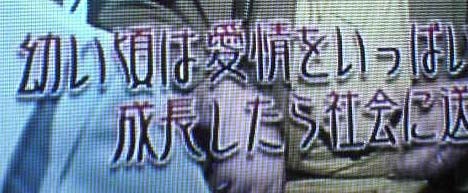
10年前のインタビュービデオを拝見して  tomoppyこと河原  2008年10月4日(土) 10:42  Mail
[タイプラボ・フォントNEWS]第58号のMLで紹介された佐藤さんの映像を拝見しました。貴兄のMLを受けるようになってから5年以上にもなると思いますが、いつも楽しみに記事を読ませて戴いています。
映像の中にお話のあった超職人気質のお気持ちは立派で、感心しました。また、どの職業についても言えることですし、Fontを制作される世界も絵画などと同様の評価がなされていることの世界だと気づかされました。今後のご発展を願っての感想でした。
メルマガもWEBサイトも、いつも文字や画像だけのお知らせですので、たまには声や映像などでリアルな感じをお伝えしたくなり、今回の記事となりました(10年以上前の映像ではリアルと言えないか…)。
メルマガで案内してから丸二日過ぎましたが、300人ほどの方が見てくれたようです。
著作権違法かどうかの判断  山田ナオタカ  2008年9月11日(木) 0:11  HP
フォントについての著作権違反かどうかの判断はどうやって付けたらよいのでしょうか。
たとえば、http://www9.atwiki.jp/gamekouryaku-knst/pages/37.htmlのサイトのように、
明らかに、
・HG明朝B
・HG重ね角ゴシックH
・HG重ね丸ゴシックH
・魚石行書?
・HG創英角ポップ体
・HG創英角ゴシック
を加工したり、
MSゴシックを代用したりするのは、
法律上、著作権に違反するのでしょうか。
サイト管理人に違反のおそれがあるので注意をしたのですが、
聞く耳を持っていただけませんでした。
注意しても駄目な、こういう人いますね…。
フォントを作る…ってことは、この程度のことだと思ってるんでしょう。
どうしても気になるのでしたら、当事者(権利保有者)に連絡して、そちらから警告してもらうしかないでしょう。
なるほど、やはりその方法になるのですね。
私も以前フォント制作に携わる機会がありましたが、
一字一字作っているということを認識してほしいと感じました。
例のサイトをさらに調べてみると、
どうやら、英文字についても、こちらのサイトのフォントを
あたかも自分の成果物のようにふるまっていることがわかりました。
http://blog.mix-tune.com/archives/319.php
このサイト、なくなったようですね。
山田ナオタカさんの行動の影響なのか、当事者からの警告があったのか判りませんが、悪質なフォント配布サイトがひとつ減ったことは確かです。
同じ管理人が、サイト名を変えて同じようなコトをしていないことを願います。
【フォントの価格ってどうなのよ】読みました。  2008年6月1日(日) 23:47
大変興味深く拝読しました。
そして世の中には “安いから” 使われるフォントが溢れているなあ、と再認識。
以外に一般の方はフォントの美醜に興味がなく、大半の書類張り紙にMSゴシック。
テレビのテロップも大半がスクリーンフォントの権利が安価なものに見えます。
確かにそれも文化の一つ、私も会社っぽい雰囲気を出したいときにわざとMSゴシックを使ってみたりすることもあります。
でも逆に美しいフォントがたくさん使われている環境だったら…。特に子どもたちには大きな影響があるような気がします。わたし個人がフォントに興味を持ったきっかけも児童文学に使われていた活版の文字、漫画のセリフの写植、絵本の文字等からでした。
一概に、安い=悪いと言えないのがフォントではありますが、「文字を読む」という、社会で暮らしていく中ですごく重要な行動を支えているものなので、もっと注目されるべきであるとは思います!
価格が高いフォントが優れている…と言い切る事もできません。
美意識とか美的感覚、機能性など、使う人によってフォントを選ぶ基準はさまざまだと思います。
・フォントの価格が、もう少し低い価格帯に収まっていれば、一般の人達にもっと興味を持ってもらえるのじゃないか。
・購入者には関係ない、制作期間や費用などを安易に価格に転嫁しないで欲しい。
そういう気持ちで今回の原稿を書きました。
【フォントの価格ってどうなのよ】読みました。  2008年6月2日(月) 19:59 [修正]
>・購入者には関係ない、制作期間や費用などを安易に価格に転嫁しないで欲しい。
作る側はなかなかサラリと言えないことなので、カッコいいと思いました。
デザインで定評のあるAppleの社長は大学でタイポグラフィを学んだことをたいそう自慢にしていて、自分の審美眼の基礎だと言ってたそうですし、毎日見るものが美しいかそうでないかということはとても重要だと感じています。
様々な価値観があることは大前提に、もっと選択肢が広がると良い、という論旨には大賛成です。
余談ですけれど、映画の字幕が手書きでなくなったり、活版の活字がなくなったり、「タンタン」の漫画のセリフを手書きで書いていた方が引退されたり、寂しいことが多いです。
本が好きで活字に親しんできたせいか、文字に触感に近いものを感じるので、好きなフォントはいくら眺めていても飽きません。
フォントの名称など知らない方でも、「好き」「嫌い」はとてもハッキリしていたりします。おそらくさとう様の仰るように、もっと好きなフォントを使うことが一般的になれば面白いなと思います。
>・購入者には関係ない、制作期間や費用などを安易に価格に転嫁しないで欲しい。
依頼された注文で、依頼者だけに提供するロゴタイプなどなら「制作期間や制作費用など」も価格に反映されて当然ですが、
フォント商品は「音楽や本や映画」などと同じように、複製されて提供されている創作物です。
多くの人に親しまれている「音楽や本や映画」などのように、一定の価格帯で提供されれば、フォントがもっと普及するのにな……というのが私の気持ちです。
今月のフォントNEWSに「春夏秋冬」が載っていてびっくりしました。(恥ずかしながら作者です。)自分は小学校に勤めています。プリントを作ったりお便りなど出したりするのに、自分の字でできたらいいだろうなあ、と思って勢いで作り始めたのですが、なにせ初めての経験で当初の予定より大幅に時間と労力を費やしてしまいました。作っているうちにだんだん字が大きくなってきて、最初に作った500字くらいは結局作り直すはめになってしまったり。それでも、なんとかぼくの目的程度は打てる字ができて、実際に使ってプリントができるようになって、ちょっと嬉しい今日この頃です。
あの字は、実はあまりに丁寧に書きすぎたせいで、普段書くぼくの字とは少し雰囲気が違ってしまっています。できれば今度はもっとのびのびと自分らしい字でフォントを作ってみたいと思ってはいるのですが、なんせあの労力をもう一度、と考えると・・・。とにかく楽しい経験をさせてもらいました。
ちなみに、「あられ」と「セプテンバー」のお試し版を使わせていただいております。「あられ」は芸術だと思います。
春夏秋冬  さとうゆたか  2008年5月8日(木) 7:39 [修正]
作業の途中で、みなさん同じように、悩んで作り直したりするんですよね。
初めての経験にしては、よくまとまっていると思います。
まだできていないはずの文字も表示されるようですが、どんな方法を使っているのでしょう?
わたしにはちょっと判りませんでした。
「あられ」気に入ってくれて、ありがとうございます。
何も分からないままに、「まるで手書きプラス」というソフトを使って作りました。「直接手書きモード」というので作ると、取り込んだ字はそのままの形で、取り込んでいない字はベースフォントにぼくのくせを反映した(?)字で表示されるのだそうで、ベースフォントにある限りの字は空白になることなく、勝手にあのような字で表示されます。
ちなみにベースフォントは「白州ペン楷書体」といいますが、作ったフォントは配布可ということです。
博物館の広報紙や学校のプリントなどでお見かけし、
セプテンバーの文字に一目ぼれして、
探して、こちらに辿り着きました。